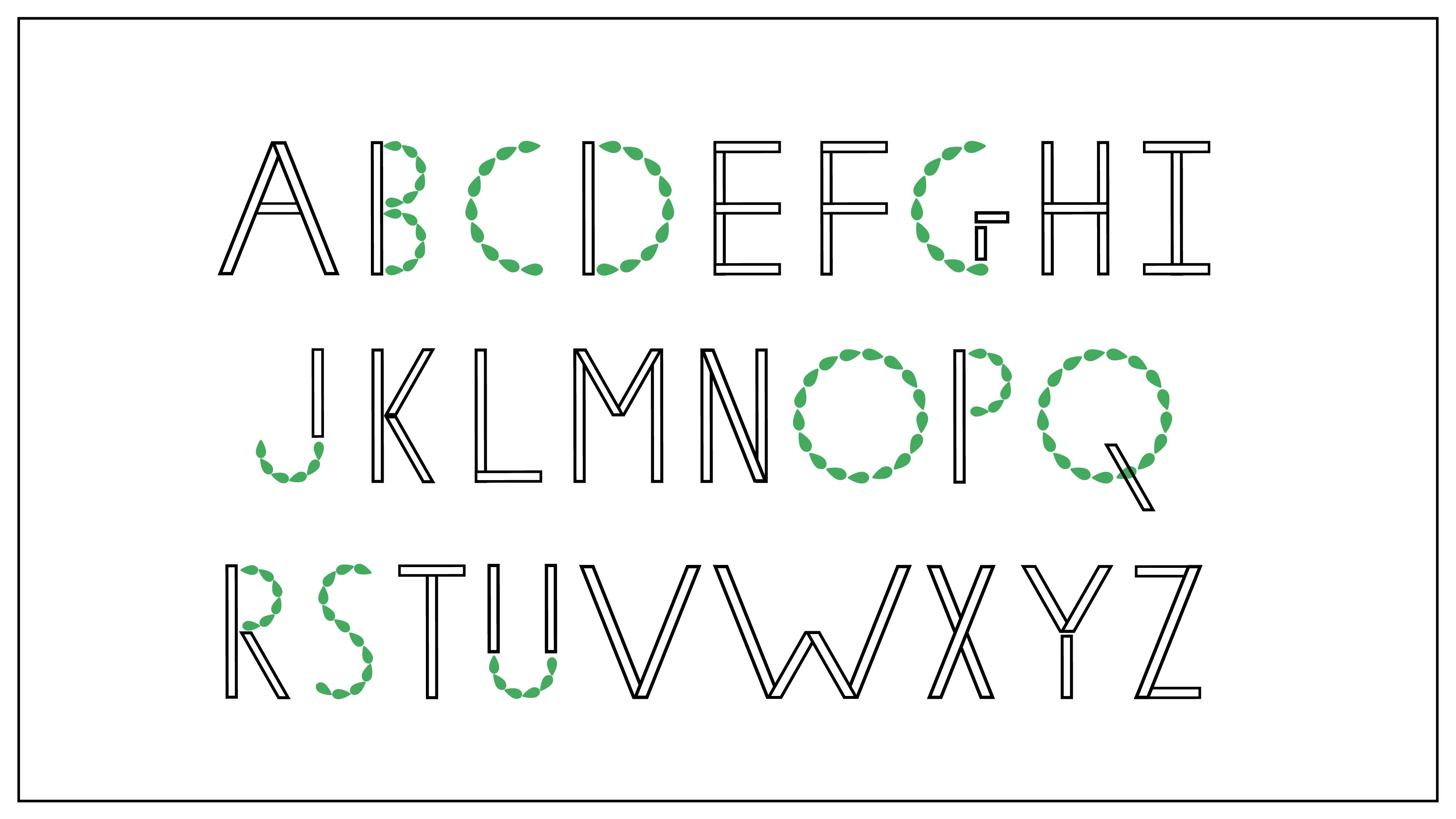
1. Einführung: Hallo und willkommen, modulare Topographie zu verletzen. Ich bin so eine Sharma, eine Motion-Designerin mit einem besonderen Platz in meinem Herzen für coole Typografie. Wenn Ihre totale Mama ist eine Art modulare Typografie ist ein großartiger Ort, um zu beginnen und Sie werden fantastische Typografie Arbeit Ihrer eigenen in kürzester Zeit. Diese Klasse lehrt die Grundlagen von modularen Typ zu machen, und wenn Sie nicht mit dem vertraut sind, was das ist, wird
es im Grunde genommen nehmen, wenn die Buchstaben aus einer begrenzten Anzahl von
Formen namens Modelle konstruiert werden . Also, im Wesentlichen, könnten
Sie einen Kreis verwenden und aufrecht. Ich gehe und mache eine ganze Schrift. Auf diese Weise sind
wir modulare Typografie. Die Buchstaben reichen von einfachen Formen in ein paar Linien von Autos, komplexere wurden mit komplizierten Formen,
Module, die schwer zu erkennen sind und viele verschiedene Module oft wollen. Sie wissen, Typenstücke basieren auf Körnungen auf jedem, den Sie lieben. Jeder Brief, entweder Allianz in das Raster von Millionen von Abschnitten Ihres Projekts durch diese Klasse wird sein, Ihren ganz eigenen modularen Typhus zu machen, einschließlich aller Spuren Buchstaben des lateinischen Alphabets. Dies mag überwältigend erscheinen, aber sobald Sie ein paar Formen haben, haben Sie bemerkt, wie ähnliche Buchstaben wie E L F I R auf der Schrift praktisch durch dieses Projekt kommen. Sie lernen grundlegende Informationen über die Zeitstruktur. Wie vereinfachen Sie die Illustration von dem, was Sie Gesichter auf ein wenig einfachen Adobe
eine modulare Schrift überall verwendet werden, wo Sie wollen. Abhängig von der Komplexität, können
Sie es für die Überschrift Teig, Spoelstra Spezifikationen, Druckmaterialien oder digital verwenden. Und wenn Sie sich ehrgeizig fühlen, könnten
Sie es sogar in einen gekämpft vor allem verwandeln. Es macht wirklich Spaß, und du kannst es nicht. Einige Papier real wurde nicht auf einige Illustrationen angehoben und eine politische Themen, um
2. Was ist ein modulares Typ?: Also bin ich so froh, dass du hier bist und du beschlossen hast, diesen Kurs zu nehmen. Bevor wir also tatsächlich unsere eigene modulare Schrift erstellen, lassen Sie uns ein wenig darüber reden, was Schriften modular macht und wie man mag, diese Modularität
sieht und was das alles bedeutet? Also, wie ich im letzten Video erwähnt habe, haben
Audioschriften einen riesigen Grat. Sie haben eine wirklich einfache Modelle, wissen
Sie, wo es so einfach ist. Das sieht eigentlich aus wie ein Gedanke, den Sie auf Ihrem Computer finden könnten, im Gegensatz dazu könnten sie wirklich, wirklich komplexe
sein . Wie für das wirklich genial damit, ist es das? Inspiriert von der Londoner Underground, wie diese Karte aussieht? Das ist also deutlich als Buchstaben erkennbar. Aber zur gleichen Zeit ist
es sehr viel eine Karte. Diese Modellierer sind so komplex, Sie wissen schon, mit den einzelnen Linien und Doppelaugen und alles und und komplexe Modelle können sehr
unterschiedlich voneinander sein . Aber diese, diese Schule, Steve Onkel über alles ist so kompliziert, wie die V's. Es ist so kompliziert, aber Sie können Dinge sehen, die wie sich wiederholende Formen sind. Weißt du, du hast eine säkulare Farm mit diesen Büchern, die immer wieder auftauchen, so wie das nicht ist. Oh, das ist ein Stichwort. Man konnte diese Ähnlichkeit dort sehen. Es gehörte immer noch dazu, Schriftkämpfer zu sehen, um ein Ei von dieser Schrift zu nehmen und von dieser Schrift, und ich habe sie in das gleiche Wort gesetzt. Sie würden wissen, dass das von zwei verschiedenen Typen ist. Aber wenn ich eine Reihe von Buchstaben vom gleichen Typ Gesicht nehme, sieht
es so aus, als ob es zusammen gehören soll, weil es als Einheit funktioniert. Weißt du, wie diese V und W, wo sie eine ähnliche Farm haben wie sie. Und so konnte man sehen, dass W im Grunde nur das ist, dass er zweimal wiederholt. Also, was wir durchmachen werden, ist, wie man diese Modularität erkennt und wie entworfen, dass es
anfänglich eine Einschränkung mit diesen
gibt. Zum Beispiel, wenn Sie etwas betrachten, das uns einfach ist, ist diese Art von einfachen ein Händler Schriftart ? Ich könnte etwas lange Worte schreiben. Vielleicht bekommst du einen Satz, bevor das anfängt zu verwirrend schwer zu sein. Aber je komplexer man geht, desto mehr muss es sein Es war wirklich sparsam und wirklich einfach. Ich meine, wenn ich mehr als das hier schreiben würde oder wenn ich etwas kleiner werden würde, würde
das wirklich,
wirklich schwer zu lesen sein. Und lassen Sie uns Ihnen hier
ein Beispiel geben. Dies ist eine schöne Schrift, die ich sagte, Sie können sehen, dass das sagt, Typ von. Ich fühle mich, als wäre das nett und groß. Aber wenn ich die Größe reduzieren sollte, schreiben ganze Sätze wie das wirklich gelesen wird. Wenn ich mir eine Art Handzettel Bank geführt oder ein Buch oder so etwas,
das ich einen Absatz hatte, würde
ich diesen Teil überspringen, wenn ich nicht gehen, um zu stehen und lesen Sie es darüber, wie Schönheit Schriften verursachen, das ist einfach zu verwirrend. Aber was geschrieben ist, ist, dass es alles Englisch ist. Es ist relativ einfach. Wenn ich das in die Zukunft verwandeln oder etwas, das leicht zu lesen ist, und das ist das gleiche Zeug, also ist es wirklich wichtig, wie Sie Ihre modularen Schriften verwenden. Es ist komplexer. Du gehst zu wirklich wichtigen. Denken Sie daran, dass Überschriften auf Banner und
großen, großen Typ ist, wo Sie Dinge wie diese verwenden möchten. Sie können es nicht vier Absätze verwenden, also gehen wir zurück zu dieser einfachen Schrift. Sie können sehen, dass das gleiche Rechteck eine Art von der Herstellung dieser ganzen Schrift ist. Sie können sehen, dass wir immer wieder die gleichen Einheiten verwenden, um die ganze Schrift zu erstellen. Und wenn ich dieses Stück von diesem Jake abschneiden würde, würde
ich das begreifen, oder wenn ich das wiederholen muss. Ich entscheidet, dass dies das eigene ausmacht und es viele reparative Formen hat, und Sie werden sehen, dass weniger immer für Morgenschriften gilt, weil Sie eine Einheit als
Modell verwenden und einen Haufen entwerfen und dass Sie das wiederholen und es drehen um und es etwas anders zu
gestalten, so dass man mit Briefen enden würde, die diese beiden anders aussehen, aber vielleicht etwas so kompliziertes betrachten und denken,
Oh, Oh, das ist ein normales Nachtgesicht, aber das ist es nicht. Die Sache ist, dass ich keinen Teil dieses Briefes lesen und ihn woanders anbringen kann immer noch etwas bekommen, das aussieht, als wäre es Teil desselben Typs Gesicht. Diese sehen alle sehr ähnlich aus, weil sie in einem ähnlichen Stil illustriert ist, und, weißt
du, da drüben ist etwas Zusammenhalt los. Aber ich kann diese Bar dieses K nicht nehmen und es in dieses l stecken. Das ist völlig anders, also werden Sie nicht versucht sein, das modular zu nennen. Aber du kannst es nicht kaputt machen. Sie können es nicht sehen, es sind Plaza-Stücke. Also ist es nicht behandelt Zeit, im Grunde genommen einen Haufen aus tatsächlichen Briefen und machte einige wirklich coole Illustrationen. Es ist wirklich schön, aber es ist einfach nicht Modellierer. Es ist also ein Teil der Ausschau nach denen, die kein Modell oder eine Schrift ist. Und das bringt uns zurück zu wie die letzte Art von modularen Schriften, die die Gitter-Basis sind jetzt zugeben, dass dieses Kastenraster, das wir hier dieses Meer haben, durch die Herstellung dieser Art von Diamantform
gemacht wird . Es ist so, als würde ich an verschiedenen Kreuzungen die Form unterschreiben, wenn jemand stirbt. Beschlossen,
Sie wissen schon, wirklich voran zu gehen, ehrlicher Schlaganfall. Mit diesen und anderen Orten haben
sie Spektakel Ding. Aber all diese Kreuze sitzen an einer Kreuzung von diesem Gitter, was diesen Brief macht. Es gibt also einen Punkt, an dem dieser Kreuzungspunkt in der Mitte des Platzes sitzt. Es ist immer an, wie eine Kreuzung, die bereits in diesem großen existiert. Ähnlich, für so etwas und Wunsch, verschiedene Teile dieser großen verschiedenen kleinen
Löcher zu füllen , macht
diese größte Formung all unsere Schrift und Sie können immer noch sehen, als ob sie nicht nur die Gitter. Sie stellen sicher, dass Teile von Buchstaben, die ähnlich aussehen wie diese Brokenness, dass Schlaganfall. Mal sehen, dass der Strom streichelt, dass e. Sie benutzen die gleiche Form immer wieder. Sie könnten es über die anderen ausfüllen. Wissen Sie, sie fügen dieses Dreieck auch für das Meer hinzu, oder sie könnten sich entscheiden, das E zu schließen, indem sie dies schließen, sie behalten diese Konsistenz und die Designkonsistenz ein großes und was Ihren
Modelltyp macht sah wirklich gut aus und gut gestaltet. Das werden wir hier drüben ähnlich ankommen. Weißt du, du musst nicht eins dieser etablierten Gitter nehmen. Du könntest deinen eigenen Griff machen und sie füllten einfach die richtigen Teile aus, um es zu den Buchstaben zu machen . Und es schreibt gerne wie eine Überschrift darin. Es würde Sinn für Sie machen, aber ein Absatz, wie ich schon sagte, würde einfach zu kompliziert werden. Also im Grunde, wenn Sie auf eine Schrift stoßen
und Sie nicht sicher sind, ob sie modular ist. Eines der besten Dinge, die du tun kannst, ist, dass du es dir ansehen kannst. Nimm das zum Beispiel. Sie können darüber nachdenken, dass es nicht so aussieht, als wäre es an irgendwelchen
Stellen aus der gleichen Neustartform gemacht. Aber dies wird zweimal wiederholt, um Ihnen sagen zu lassen, dass es auf den Kopf geht, um dieses M zu machen, und Sie sehen die gleiche sich wiederholende Form und so dass sich wiederholende Form das Modul ist und wir
eine Reihe von verschiedenen Modulen haben und, wissen
Sie, Sie sind alle auf verschiedene Arten angeordnet, um diese ganze Schrift zu machen und zu machen. Aber ich sitze hier und seziere das, und ich würde am Ende Puzzleteile sehen, und diese Puzzleteile sind miteinander verbunden, um verschiedene Buchstaben zu machen. Und diese Puzzleteile sind Montiels Gitter ein großartiger Ort, um zu beginnen, weil Gitter von
Natur aus sind , eine sich wiederholende Form, die gleiche Box wie hier drüben, diese Box Great. Diese Box wird immer wieder und immer wieder wiederholt, es ist das Gleiche. Ähnlich, mit dieser Form hier ist es das gleiche, immer wieder
wiederholt. Der Grund für Schriften modular ist, weil Sie in der Lage sind, die gleichen Formen zu nehmen und
sie an bestimmten Orten zu wiederholen , um etwas, das ein wenig anders aussieht, und Sie können eine Reihe von anderen Puzzleteilen nehmen. Setzen Sie sie in verschiedenen Konfigurationen zusammen und Sie am Ende mit verschiedenen Buchstaben und Rastern. Luft so ein großartiger Ort, um zu beginnen, weil Gitter von Natur aus die gleiche schlagende Form immer
wieder sind . Wenn du es fühlst, fühlst du dich immer in der gleichen Form, oder du richtest deine Form immer wieder an diesem Gitter aus. Sie haben automatisch etwas, das eine schlagende Form ist, was wir wollen. Weißt du, wir wollen etwas, das wir in Stücke zerlegen können, und das wird dir großartig geben. Nun, da wir herausgefunden haben, wie Modularität funktioniert, gehen
wir zur eigentlichen Typografie über und wie Typografie funktioniert, wie ihre Struktur ist. Wie soll man eigentlich dieses Alphabet nehmen? Alle Buchstaben ein schwindelig und lernen, sie alle in diese Art von modularen
Puzzleteile zu sehen , so dass Sie beginnen können, Ihre eigenen zu entwerfen
3. Die Struktur der Typografie: Nein, ich benutze hier einen Haufen Illustrator, und das kann wirklich überwältigend werden. Aber wenn wir tatsächlich in die spannende eigene Schrift springen, werde
ich durch, Illustrator, all die Grundlagen, all das einfache Zeug, das du wissen musst. Wenn Sie überhaupt keinen Illustrator kennen, Sie
nicht überwältigt von dem, was ich hier mache. Dies ist nur, um zu erklären, wie alles funktioniert. Jetzt, wo wir die Modularität herausgefunden haben, gehen
wir zur Typografie über. Das coole an dem lateinischen Alphabet ist, dass das ganze Alphabet, ich meine, alle 26 Buchstaben. Sie können alle in zwei Arten von Strichen geraden und gekrümmten unterteilt werden. Jetzt gibt es drei Arten von geraden Strichen. Du könntest horizontale haben, bequeme, und du könntest diagonale haben. Und gekrümmte können offen oder geschlossen sein. Und im Grunde, mit diesen fünf Arten von Strichen, können
Sie jeden Buchstaben auf Englisch aus machen. Also lasst uns das jedes Mal eine Chance bekommen. Das ganze Alphabet hier, richtig? Und so ist das Ihre Schriftart. Das ist Andiwal Glanz. Aber ich konnte jeden Buchstaben nehmen und ihn in diese Puzzleteile oder
Striche C zerlegen . Wir haben H aus zwei diagonalen Strichen und einem horizontalen Strichen gemacht. Es gibt eine vertikale wollte gebogene Striche öffnen und ähnlich sein. Es gibt nur einen Öffnen-Kurvenbereich und sehen. Und Sie können das gesamte lateinische Alphabet so aufbrechen. Das Ganze ist aus diesen Puzzleteilen gemacht. Das gesamte lateinische Alphabet kann so aufgeschlüsselt werden. So wie J u und s alle diese offenen gebogenen Striche verwendet. Richtig? Also haben Sie dieses J und öffnen Armstrong ist mit einem vertikalen gepaart. Oder verzweifeln Sie auch ein bisschen. Vertikale und s ist zu Öffner Striche mit einer Diagonale. Und so lassen Sie uns einen Blick auf, wissen
Sie, einige Dagnall-diejenigen, die A und Z. Er war die Daigle-Schläge und repariert mit diesen horizontalen geraden Strichen ähnlich mit em. Und weißt du, da gibt es dich, die sie mit geraden diagnostiziert haben. VW als Nächster. Sie brauchen niemanden anderen. Sie haben nur diagonalen Straßenstriche und K und warum sie sind ein bisschen ein besonderer Fall, denn obwohl sie alle diese diagonalen Striche wie die Luft immer noch diagonalen
Striche verwenden . Okay, aber wenn Sie eine gesuchte Schrift entwerfen, müssen Sie vorsichtig sein, wenn Buchstaben wie diese , die eine bestimmte Art von Strich verwenden. Aber vielleicht gibt es die gleiche Länge für den gleichen Grad der Kurve auf und sind die gleiche Größe weil lassen Sie uns einfach einen Blick darauf werfen. Wenn du ein sehr schönes Sterben entworfen
hast, weißt du, Designschule, Dad will dich und du willst es in all die Briefe setzen, die ich Module benutzt habe, die du einfach so lange richtig
machst und du kannst es in all diese stecken Briefe und du kannst
wie
ein Z.machen wie ein Z. Weißt
du, du hast deine Enden und deine VWs und Exes, die jeden anderen benutzen, den
du kennst , du hast sie. Was passiert, wenn du verfallen könntest, oder warum? Warum braucht langwierige kleine und auch K.
Kann das nicht in K setzen, denn was passiert, wenn man wirklich versucht, K aus einem von
diesen zu machen ? Ich habe immer noch einen Schuss. Wenn du versuchst, eine davon aufzupassen, wirst
du mit einer riesigen K gute Größe enden, was du? Das ist eine große, große K. Sie betrachten, vergleichen Sie das mit der Größe Ihres VW-Nexus, und Sie sind nicht wirklich in der gleichen Nähe mehr. Was passiert, wenn man ein Wort mit dieser Schrift buchstabiert? K ist größer als alles andere, was wirklich,
wirklich schlecht aussehen wird . Also, was Sie tun ist, Sie stellen sicher, dass Sie Buchstaben wie diese haben, die kleinere
Längen oder Größen von der gleichen Art von Strichdesign,
ein anderes Modell für sie oder Italien verwenden Längen oder Größen von der gleichen Art von Strichdesign, . Irgendetwas glaubt wirklich ähnlich. Also, als ob ich über die diagonalen Schriften erwähnte. Nehmen wir einen anderen Ort, wo das Problem auftreten könnte. Sie haben einen offenen Kurvenstrich. Dies wird viel Platz im lateinischen Alphabet verwendet, zum Beispiel im Meer oder behindern. Aber das Problem hier ist, dass, wenn du C und P wärst, die gesamten Wettenden die gleiche Länge haben wie deine Kurven. Schlaganfall allein ist eine wirklich andere Ereignisse, wissen
Sie. Es ist schnell die gesamte Höhe des Buchstabens in C, aber nur verbringt halb gestorben Brief in Schlüssel. Und so gibt es ein paar Buchstaben, die dieses Problem in PB haben und es nimmt die halbe Höhe von einem Buchstaben ein,
und in C,
D und Gnimmt
es die ganze Höhe des Buchstabens und in C, D und G ein. Jetzt könnten Sie sagen, warum das ein Problem? Es ist erledigt. Offener Bordsteinschlag. Entwerfen Sie einfach ein Modul, das funktioniert, ist ein offener Fluch Schlaganfall. Und ich sollte in die richtigen Briefe kommen. Okay, nun, lassen Sie uns das eine Chance geben. Was passiert, wenn Sie entwerfen? Weißt du, du hast dieses schöne Kurvenmodell hier drüben, okay? Entwickelt dieses Audio, und Sie wollen es überall verwenden, als offene Auto Hub wird im englischen Alphabet verwendet. Nun, wenn du das gerade entworfen hast
und dann so bist, okay, ich muss voll sein. Lassen Sie es jetzt. Also werde ich es einfach in voller Länge schaffen. Nun, das sieht schrecklich aus. Wenn Sie versuchen, ein Meer daraus zu machen, oder ein D sind, dass es viel zärtlicher aussehen wird als all Ihre anderen Wettenden, und es wird nicht so gut aussehen. Sie müssen also sicherstellen, dass ein anderes Modell entworfen wurde, das nicht im gleichen
Design-Sinn wie Ihr kleines funktioniert , aber entworfen wurde, um in dieser Größe zu arbeiten. Es gibt nur zwei Stellen im lateinischen Alphabet. Nur zwei Buchstaben, die geschlossen Vorhang Strich O und Q jetzt in einem 26 Buchstaben Alphabet verwendet, zwei Buchstaben ist nicht sehr viel. Das ist 1 30 das ganze Alphabet. Nun, wenn 1/13 so ein kleiner Bruchteil von Ihrer ganzen Schrift anders aussieht als ein anderes Treffen, wird
es nach dem Seltsamen suchen. Nehmen wir an, Sie beginnen Wort mit O que Wie Oktopus oder Königin. Es könnte ziemlich cool aussehen. Ich bin der Geist, die Hauptstadt. Aber was passiert, wenn O. R. Q. mitten im Wort
auftauchte? Es wird sich nur anschauen. Sie müssen also sicherstellen, dass das offene Bordsteinmodul, das Sie machen möchten, sicherstellen, dass das Job-geschlossene Kurvenmodul in der gleichen Welt in der gleichen Sprache funktionieren sollte . Das sieht so aus, als gäbe es einen offenen Kurvenstrich und es gibt eine geschlossene Kurve, und sie sehen aus, als ob sie in die gleiche Zeitfläche gehören. Wenn Sie also anfangen, seine Sachen zu entwerfen, ist
Designkonsistenz der Schlüssel. Wenn dein Zeug nicht konsistent ist, wird
es einfach schlecht aussehen. Wie, was passiert, wenn Sie eine offene Kurve haben? Stroke Sieht so aus, aber Ihre Kleidung erste Reihe sieht so aus. Es wird einfach wirklich fehl am Platz aussehen, wenn Sie anfangen, Dinge so gewünscht zu buchstabieren . Konsistenz ist der Schlüssel. In ähnlicher
Weise geraden Strichen entwerfen
Sie beigeraden Stricheneinen schönen vertikalen geraden Strich. Und du bist wie, OK, ich bin damit fertig. Ich werde es einfach nach innen drehen und meinen horizontalen geraden Strich leicht peasy machen, wie das Problem damit ist, wenn ich nur meine vertikalen Striche benutze und sie mit,
du weißt schon,
einfacher schwarzer Linie kombiniere du weißt schon, . Ich habe meine Fünf, die ein Alter machen. Aber was passiert, wenn ich es versuche? Verwenden Sie diese beiden Sehnsüchte, um h ich am Ende mit einem
wirklich, wirklich breiten h. Es sieht irgendwie seltsam aus. Es sah nur aus wie ein Alter. Und es gibt andere Briefe, die das auch benutzt haben. Du bist leichter f sicher. Ages werden wirklich breit Wenn Sie am Ende versuchen, die gleiche linke oder das gleiche verwenden Sie nur auf seiner Seite für eine horizontale Meerenge Gauner gekippt. Du willst also sicherstellen, dass deine Höhen und dein Verstand und alles
richtig funktionieren . Du hast also Lockerung. Du hast absolut Recht. Das sieht so viel besser aus, wenn es nur die Hälfte der Geburt von Ihrer Größe
ist, es fängt an, wie eine anständige Schrift zu sehen. Nehmen Sie alle diese Buchstaben, zum Beispiel, E f h l t. Und sehen Sie alle diese horizontalen geraden Strich verwendet, all diese Darlehen und groß. Damit ich die gleiche Mom entwerfen konnte, die du in all diese Briefe gesteckt hast, und es sollte funktionieren. Aber es gibt einige spezielle Anwendungsfälle, wenn es um diese horizontalen geraden Striche geht. Du hast G, wie ich. Jeanne. Ich benutzte diese horizontalen Streifen manchmal gebrochen. Und im Fall von GM haben
Sie eine vertikale. Das ist das gleiche als horizontale, Ihre vertikale, dass Ihr Design wahrscheinlich diese Höhe haben wird, weil all diese Buchstaben sie in dieser Höhe verwenden. Aber G, es braucht eine kürzere. Und dieses hier haben wir nicht manchmal der Grund, warum ich das sage, ist, weil ich uns diese
Schriften ansehen . Das sind eigentlich einige Schriftarten, die ich g und ich bin. Und schauen Sie sich dieses G. In diesem Fall verwendet
es einen kürzeren Hub horizontal und vertikal und in diesem Fall wird nur
Kurvenschlag öffnen . Aber wir bestellen einfach etwas, das Sie nicht brauchen. Eine vertikale Straße hier. Hier drüben will
es überhaupt keine horizontale Straße benutzen. Wir haben nur eine vertikale Straße eins. Also abhängig von Ihrer Schrift und je nachdem, was Sie es wie Ihre G My
Change gestalten möchten . Das Gleiche gilt für I. In einigen Fällen war
ich nur ein vertikaler, gerader Schlag. Aber manchmal wissen Sie, einmal eine Bar, der Arzt unten. Und dafür brauchen Sie eine horizontale Straßen. Rocca geht es gut und manchmal könnte das dasselbe sein. Aber nicht auf der Seite mit dem High Charton. Aber in einigen Fällen möchten
Sie vielleicht etwas anders gehen. Design weise, Ihre Autos von der Straße, Seile sind dünner als die vertikalen geraden Striche. Ihr Design kann sich also ändern, was vollständig von Ihrer Schrift abhängt. Und welche Art von Design Ihre Arbeit auf, Aber denken Sie daran, dass diese Luft, einige spezielle Fallbuchstaben und Sie müssen möglicherweise einige spezielle Module für sie entwerfen. Jetzt kommen wir zum Licht des speziellsten Falls. Das ist dieser kleine Spiral-Typ, den ich entworfen habe, nur um Ihnen eine Idee zu geben, wovon ich
spreche , Ihre speziellen Anwendungsfälle, wenn Sie Sachen wie warum que que Sie wissen alle diese in
Farbe haben ? G A. Ich all diese, die sich manchmal gewöhnen, aber Sie wissen, dass diese Art von lassen Sie uns an vielen Orten gewöhnen. Sie könnten ein cooles,
dekoratives Modell wie dieses entwerfen und es an all diesen Orten anschließen. Und der Grund, warum ich sage, dass Sie wahrscheinlich sollten, obwohl Sie eine sehr leicht
mit Ihrer Diagonale auf Ihrer Seite entwerfen könnte , ist bis eins. Möglicherweise möchten Sie dieses dekorative Element an mehr Stellen als nur dem
Minimum verwenden , wo es benötigt wird, denn je mehr Orte Sie Modell für den Typ verwenden, desto mehr wird es erstellt. Das Design Konsistenz über den gesamten Typ ist. Wenn Sie also anfangen, Buchstaben sind Wörter zu schreiben, wird
es so aussehen, als ob es sich in der gleichen Schrift und in derselben Welt sehnt. Wenn ich also meinen Pyro-Typ mitnehme und ihm „Warum „oder „K „oder „Q „und „Jeans A „und „ich... sieht
er so aus, als ob sie in derselben Nähe gehören, ? So könntest du so etwas machen und mit etwas Coolem enden, wenn ich einfach
damit arbeiten würde. Okay, das ist eine Arbeit. Aber der einzige Grund, der zusammen arbeitet und es sieht so aus, als ob es in die gleiche Welt gehört, ist weil ich den gleichen Spiral-Typ wieder benutzt habe. Geh einfach etwas Polieren. Ich meine, diese Diagnoseschläge sind nicht jedes Mal der gleiche Winkel, und das werden wir durchmachen, aber du kannst ihn so benutzen.
4. Gestalte Module: so ist die Zeit für uns endlich gekommen, Module zu machen. Wie ich im vorherigen Video erwähnt habe, gibt es Feuer grundlegende Arten von Strichen, und es ist eine gute Idee, ein Modell pro Hub zu erstellen, wenn Sie anfangen und dann
alle benutzerdefinierten Modelle erstellen , die Sie auf dem Weg benötigen, Sie möchten beginnen mit einem geraden horizontalen Strich, einem vertikalen Straßenstrich, einem diagonalen, geraden Strich, einem offenen Kurvenstrich und einem geschlossenen Kurvenstrich. Sobald Sie diese an Ort und Stelle haben, können
wir damit beginnen, Zollstriche zu Ihrem Modell Skin zu machen. Sieh
mal, wie du es willst. Wenn Sie für das Team starten möchten, ist
das OK. Sie können mit einem künstlerischen Thema beginnen, wenn Gothic oder Art Deco. Oder Sie können einen zentralen Fokus wie etwas Zufälliges wählen, vielleicht Wolken und entworfene Schrift um das. Wie ich im vorherigen Video erwähnen würde. Es ist völlig in Ordnung, wenn Sie nichts über Illustrator wissen, der in diese Klasse kommt. Aber für die Zwecke dieses Videos, fangen
wir auf dem Papier an. Alles, was Sie brauchen, ist Bleistift und Papier. Ich schlage vor, mit jedem Team oder Thema zu beginnen, mit dem Sie sich entschieden haben. Du musst es nicht tun. Dies ist nur zum Spaß, Sie können rein dekorativ gehen. Das ist
auch kein Problem, und diese Zeichenmodelle zu machen, von denen Sie gesprochen haben. Sobald Sie diese haben, würde
ich vorschlagen, sie auszuschneiden und sie in verschiedenen Konfigurationen zu platzieren, um zu versuchen,
die Buchstaben zu machen . Wenn dir die Art und Weise gefällt, wie die Dinge laufen und du das Gefühl hast, dass du genug Module hast, ist
fünf gut. Wenn Sie das Gefühl haben, zusätzliche Module wie kürzere Diagonalstriche für K zu machen und warum oder wenn Sie spezielle dekorative Module machen wollen, wie ich am Ende des letzten
Videos hatte , um vielleicht am Ende Ihrer Hinweise oder als Akzente auf Ihren Augen zu verwenden, Dies wäre die Zeit, das zu tun. Sie können für so viele Module gehen, wie Sie wollen, also schlage ich vor, nicht zu über Bord zu gehen. Aber ein Minimum von fünf ist erforderlich. Wenn Sie feststellen, dass Sie stecken bleiben, schlage
ich vor, ein Thema zu sprechen. Es muss gar nichts zu kompliziertes sein. Sogar etwas so einfach wie Blätter wird dio, vielleicht das Team wie Blätter. Sie hätten ein oder zwei Modelle, die deutlich Blatt wie sind, und der Rest würde als einfachere Akzente dienen, vielleicht ähnlich in der Farbe zu verlassen oder einfach nur ist eine schöne, kostenlose Farbe, um die Sie Ihre gesamte Taipeh gestalten können. wie immer Weniger istwie immermehr. Wenn du das Gefühl hast, dass du zu viel in deine Schrift
steckst, wirst du es wahrscheinlich tun. Ich könnte später schwer zu lesen sein. Sobald Ihre Module alle entworfen sind und Sie sie in Ihre verschiedenen Buchstaben gesetzt haben und Sie wissen, wie alles aussehen will. Machen Sie ein Bild von jedem Modul separat mit Ihrem Telefon oder einer Kamera, von der Sie bequem Bilder auf Ihren Computer hochladen können. Von dort aus werden
wir es zu Illustratoren bringen, damit wir anfangen können, es digital zu gestalten.
5. Gerades Stroben erstellen: Jetzt, wo wir unsere Modelle auf Papier entworfen haben, werden
wir in Illustrator springen. Ich werde Schritt für Schritt alles durchgehen, was du brauchst. Wenn Sie also mit Illustrator ein wenig vertraut sind, könnte
dies singen, aber langsam für Sie. Aber wenn Sie völlig nackt waren, Illustrator, werde
ich alles durchgehen, was Sie brauchen, um Ihr eigenes modulares Tempo zu bauen. So sieht der Home-Bildschirm aus. Wir werden voran gehen und drücken, neue Schaltfläche
erstellen. Nun, das ist meine Schnittstelle. Ein Illustrator. Sobald Sie über Ihre Bilder von Ihrem Handy oder Ihrer Kamera bekommen, möchten
Sie sie in Illustrator zu bringen. Dafür gehen
wir zu einer Datei Ort oder Sie können die Shortcut-Shift-Steuerung P verwenden. Platzieren Sie es einfach. Da ist ein Foto. Wie Sie sehen können, habe
ich ein Foto gemacht, das nur eins von jedem Modell hat. Ich werde dieses Bild als Referenz verwenden, also gehe ich zu meinem Ebenen-Panel direkt hier. Wenn Sie eines dieser Panels benötigen, können Sie zum Fenster gehen und auf das Paddel klicken, das Sie benötigen. Ich möchte zu meinem Ebenen-Panel gehen und ich werde hier schnell verdoppeln, was es
Referenz sein wird , und ich werde diese Ebene jetzt suchen. Ich kann es überhaupt nicht bewegen, und das wird wirklich hilfreich sein, weil wir andere Dinge darüber hinaus machen , die
fortlaufend zu bewegen,damit das nicht mit uns kommen wird. Ich werde diese Schaltfläche drücken, um eine neue Ebene zu erstellen, und ich werde anfangen, meine Module und Illustrator auf diese Weise zu machen. Es sei denn, Sie wollen, ist ein
sehr, sehr einfach Sie werden mehr benötigen als nur das Rechteck-Werkzeug oder die Ellipse, um Sie werden etwas mehr benutzerdefinierte benötigen. Wenn Sie einfach ein Rechteck benötigen, konnte einfach auf das Rechteck geklickt werden, und Sie könnten ziehen und machen, was Größe Tatsache mir gesagt wird, dass Sie wollen. Wenn Sie ein perfektes Quadrat machen wollen, nur trocken Hit Verschiebung zur gleichen Zeit und Sie sind Platz wird perfekt sein. Ebenso können
Sie zum Ellipsen-Werkzeug wechseln, wenn Sie jede Ellipse abschleppen möchten, die Sie erneut möchten. Wenn du dich verschieben
würdest, machst du einen perfekten Kreis. Wahrscheinlich werden Sie mehr brauchen als diese grundlegenden Formen,
und das ist, wo das Stift-Werkzeug ins Spiel kommt. Alle diese Buchstaben in Klammern, die neben dem Namen erscheinen. Wenn Sie den Mauszeiger über ein Werkzeug bewegen, sind die Tastatur-Shocker, die Sie verwenden, um es wirklich schnell zu verwenden . Zum Beispiel könnte
ich einfach auf die Tastatur pinkeln und ich bekomme mein Benzin. Der Weg zum Stiftwerkzeug funktioniert ist, dass ich auf eine Stelle klicke, an der ich einen Punkt beim Ziehen machen möchte, um die nächste auf den Linienformen zwischen diesen Punkten zu machen. Auf diese Weise kann ich das machen, was ich will. Und wenn ich auf den ersten Punkt zurückkomme, sehen
Sie diesen kleinen Kreis und ich klicke wieder und es wird eng geformt. Wenn ich es offen lasse, wird
es weiterhin versuchen, das nächste Bit von der Form weg von hier zu ziehen. Wenn Sie Kurven Dinge mit mental machen möchten, können
Sie auf ziehen klicken. Diese geben Ihnen diese Griffe. Diese Griffe werden als beschäftigt A Handles auf bezeichnet, und Sie können sie verwenden, um die Kurve von etwas zu steuern. Diese mathematischen berechnen, was die Krümmung von der Linie vor uns sein wird, und Sie bekommen schnell und Drachen, um diese Kurve zu machen, und Sie könnten unsere Chips so machen. Seine so wollen wieder, Ich verbinde mich, um diese Werkzeuge auszuwählen, Ich esse die oder Sie können auf das Auswahlwerkzeug klicken. Dadurch wird alles ausgewählt, was Sie wollen. Wenn Sie entfernt werden, können
Sie darauf klicken und es wird die gesamte Form zusammen klicken. Dies unterscheidet sich von dem Direktauswahlwerkzeug, dem Sie einzelne Punkte beim Bewegen nur auf eigene Faust treten können. Aber Sie können mit diesem Wahlzehen nicht tun. Ich kann keinen einzelnen Punkt bewegen. Ich muss die ganze Form verschieben, und Sie können die Rücktaste oder Löschen auf Ihrer Tastatur verwenden, um alles loszuwerden. Also fangen
wir mit diesen grundlegenden Werkzeugen an, unsere Schiffe ein wenig zu verfolgen. Ich möchte meine horizontalen vertikalen und diagonalen Striche. Drei einfache Rechtecke ohne Farbe in der Mitte streichen nur Linien. Also gehe ich zu meinem Rechteck-Werkzeug auf. Ich werde etwas über das hinwegziehen. Ich werde es jetzt loslassen. Haben Sie ein Rechteck, aber ich möchte Justin Umriss in Illustrator. Eine einfarbige Farbe in der Mitte wird als fehlgeschlagen auf einem Umriss bezeichnet wird als Strich nach oben. In meiner Farbe sind meine Farbfelder Panel. Ich kann sehen, dass diese Erfüllung auf diesem ist ein Schlaganfall. Wenn ich auf das Feld klicke, kann
ich es in die Farbe ändern, die ich sein wollte. Und wenn ich nicht füllen will, kann
ich einfach kein Gefühl auf. Und jetzt haben wir eine Form ohne Gefühl und keinen Schlaganfall. Ich will, dass mein Schlaganfall schwarz
ist, also werde ich Schlaganfall treffen. Und was dann? Schlag schwarz. Wenn ich nun mein Auswahlwerkzeug drücke, das nur V Tastatur ist und wegklicke, kann
ich sehen, dass es einen Strich um ihn herum hat. Ich kann die Dicke des Strichs ändern, indem ich auf die Strohplatte gehe und den Wechsel auf eine
Gewichtszunahme wartet . Ich schwinge meinen Schlag dicker. Im Moment hat
mein Schlag scharfe Ecken. Wenn ich darauf klicke und die Ecke
ändere, bekomme ich runde Ecken. Für den Moment möchte
ich ihnen eine scharfe Ecke halten. Wenn ich eine ähnliche Technik verwende, um meinen vertikalen Hub zu machen, wird
die Dicke dieser beiden nicht gleich sein. Ich möchte konsequent bleiben, also werde ich es nicht so machen. Ich werde dies duplizieren, ändern Sie es so, dass es die richtige Länge ist, um früher zu duplizieren, wenn Sie darauf klicken. Ich werde Option oder Ault auf der Tastatur nehmen und ich werde diese Doppelpfeile bekommen. Das bedeutet, dass überall dort, wo ich diese neue Form nehme, die Leute dupliziert haben. Also werde ich einfach wegziehen und es gehen lassen und ich werde eine andere Form haben. Ich kann das zu meinem senkrechten, geraden Strich überführen. Ich werde es um 90 Grad drehen. Ich wollte perfekt vereinte Abschlüsse sein, also werde ich mich verschieben. Du machst es perfekt und gut. Richten Sie es aus und ich möchte die Breite überhaupt nicht ändern. Ich möchte nur die Länge ändern. Aber weil ich so vergrößert bin Outbreak jetzt zeigt es mir nur diese diagonalen Steuerungen auf dem mit Kontrolle. Weil das so lang ist. So wird es wieder aufgenommen. Ich werde Befehl plus auf Mac oder Control Plus auf einem PC drücken. Und jetzt bin ich nah genug, dass ich diese vertikalen Manipulatoren sehen kann. Also werde ich nur ziehen das machen es lange genug. Also, jetzt ist mein mit die gleiche geblieben wie meine horizontale. Wenn ich schwenken möchte, kann
ich die Leertaste drücken, die das Handwerkzeug vorübergehend aktivieren würde, greifen und bewegen, wenn ich den Griff dauerhaft aktivieren möchte. Ich traf H und ich kann immer in der Hand Werkzeug sein, aber Raum ist ein netter Trick. Kann Befehl minus drücken, um zu verkleinern. Ich nehme diese und alte und ziehe sie hierher. Nun, wenn ich das einfach um ein wenig rotiere, werde
ich diese flachen Tasten nicht so bekommen, wie ich es will. Also werde ich Z kontrollieren, dass wir zoomen, damit ich sehen kann, was ich tue. Ich gehe zu meinem schiere Tool und ich werde auf Gehe zu Hit Enter klicken. Jetzt kann ich das Haus kontrollieren, das ich teilen wollte. Ich wollte einen 30-Grad-Winkel teilen. Ich werde überprüfen, um sicherzustellen, dass es so aussieht, wie ich es wollte. Guter Schlag. OK, jetzt ist mein Titel perfekt geteilt. 30 Grad. Ich wollte
jedoch umgekehrt sein, also möchte ich mein Reflection-Tool verwenden. Ich kann O auf der Tastatur verwenden oder ich kann hier wieder zu meinem Reflektierungstool gehen, ich werde die Mitte treffen. Ich muss eintreten und es wird vertikal reflektiert. Ich könnte auch horizontal reflektieren, wenn ich will. Ich möchte eine Kopie davon machen, weil ich will, dass eine Seite diesen Weg geht und die andere Seite diesen Weg geht. Also würde ich Copy drücken. Und jetzt muss ich, dass ich mein Auswahlwerkzeug drücken könnte. Das ist V auf der Tastatur. Ich bewege das weg und jetzt habe ich meine zwei diagonalen Striche in beiden Richtungen. Jetzt setzen meine diagonalen geraden Striche auf meinen horizontalen geraden Strich auf meinen vertikalen
Straßenstrich sind alles perfekt mit dem Teil. Sie sind perfekt geschoren, wo sie auf ungefähr dem richtigen Land sein müssen. Wir können diesen Führer immer so anpassen, wie wir es im nächsten Schritt tun werden.
6. Vereinfache Illustrationen und gebogene Stroben: jetzt gesendet, um unsere gekrümmten Striche zu machen. Jetzt werde ich mit der Blatt-Sache gehen, die Dr. Aber aus dem vorherigen Video,
das ist meine schreckliche Skizze aus dem Mietvertrag. Das erste, was ich tun werde, ist eigentlich einzigartig. Eine Blattform. Dafür werde
ich mein Stiftwerkzeug benutzen, komm rüber zu diesem Teamstück. Ich werde nur ein Standard-Grün nehmen, nur damit ich sehen kann, was ich tue. Es ist nicht der Begriff weiß, und ich werde die beschäftigten Griffe verwenden, die ich sprach, um ein halbes Blatt zu machen, weil ich es
perfekt reflektieren konnte , so dass ich Shift verwenden konnte, so dass es perfekt gerade steht und erstellen, Aber ich fühle mich wie es ist perfekt halb Blatt. Da dies los wird, werde ich V schlagen, so dass es seine eigene hält sogar als eine offene Form und ich werde wegklicken. Jetzt sehe ich, dass ich ein halbes Blatt habe, aber ich brauche die andere Hälfte. Also werde ich das wieder nehmen Hit Oh, für mein Reflexionswerkzeug. Ich werde eines dieser Enden verwenden, weil dies der Zugang ist, den ich
reflektieren möchte . Ich würde hier Option oder Schraube treffen. So wurde es perfekt an diesem Rand reflektiert. Ich will ein Exemplar, damit ich es kopieren kann, und ich werde einen perfekten Häuptling haben, der hineinzoomt. jedoch sehen, Ich kannjedoch sehen,dass dies immer noch nicht geschlossene Form ist, denn wenn ich ausgewählt habe, werden verschiedene Hälften separat ausgewählt. Ich kann immer Drachen zusammen gewählt werden. Aber ich möchte ein Blatt kaufen, um eine warme Form zu sein, so dass ich es manipulieren kann, wie ich will. Also, dafür werde
ich in zu wiegen, um die Kanten zu finden, wo diese Teile verbinden. Ich werde mein direktes Auswahlwerkzeug nehmen, das mein Andi ist, ziehe diese beiden Punkte zusammen, ich werde Steuerung J für Join treffen. Nun, diese beiden Punkte wurden zu einem verbunden. Wenn ich das mit meinem Direktauswahlwerkzeug auswähle,kann
ich sehen, dass es ein ganzes Schiff ist, das ähnlich gemacht wird,
wenn ich zu diesem unteren schwenke,muss
ich diese beiden auch hier verbinden. Wenn ich das mit meinem Direktauswahlwerkzeug auswähle, kann
ich sehen, dass es ein ganzes Schiff ist, das ähnlich gemacht wird, wenn ich zu diesem unteren schwenke, Dies sind zwei getrennte Pfade. Jemand traf mein direktes Auswahlwerkzeug, ziehen Sie über nur diese beiden Punkte, die
Kontrolle J.hatten Kontrolle J. und jetzt ist dies auch ein Punkt. Ich werde wieder verkleinern, damit ich sehen kann, was ich über dieses ganze Blatt schlecht mache. Wählen Sie dieses Blatt, Andi, tauschen Sie meinen Strich und fühlen Farben, indem Sie dieses kleine Symbol hier. Jetzt habe ich keinen Schlag auf diesem Blatt. Und nur um mein Blatt zu füllen sieht ein wenig aus. Obwohl irgendwo, um zu meinem Direktauswahlwerkzeug zurückzukehren, passen Sie dies
einfach ein wenig an, indem Sie die Iraker verwenden. Nun, ich mag die Art, wie das aussieht, aber ich habe das Gefühl, dass dieser Tipp zu scharf ist. Also werde ich dies mit meinem direkten Action-Tool auswählen. Das ist ein auf der Tastatur, nicht mein Auswahlwerkzeug. Also werde ich mein Direktauswahlwerkzeug verwenden, um einen dieser beschäftigten Griffe zu greifen und ich kann ihn wegbewegen. Aber ich wollte ein perfekter Winkel sein, damit ich ihn im gleichen Winkel in die andere Richtung bewegen konnte. Also hatte ich eine Verschiebung, die sich perfekt 45 Grad entfernt bewegte. Ich mache das Gleiche auf der anderen Seite. Jetzt siehst du dieses kleine, was ich hören kann, ich kann das nehmen und ich könnte es benutzen, um mein Blatt ein wenig zu weich zu machen. Klicken Sie weg. Ich mag diese Form. Ich denke, es würde sich schön wiederholen. Ich kann die Farbe von diesem Grün manipulieren, aber ich möchte Mit meinem Farbfeld, Ich kann sie auf Rot,
Grün oder Blau in diesem manipulieren . Oder ich kann hier nach oben gehen und dies in Farbton,
Sättigung,
Helligkeit oder sogar schöne Farben ändern Sättigung, . Ich werde HSP wirklich schnell setzen. Auf diese Weise kann ich einfach den Farbton ändern, aber ich möchte bleiben. Das grüne Spektrum kann verändern, wie gesättigt meine Arenen sind, wie hell es ist. Das ist ein gutes Grün. Ich denke, es ist nicht zu hell, nicht zu übertrieben. Aber es ist schön und lebendig. Würdest du wegklicken, weil mein Leben fertig ist? Eine gute Faustregel ist, wenn Sie etwas machen, das Sie einen Illustrator
mögen, ändern Sie es nicht sofort. Wenn Sie es ändern möchten, verschieben Sie es um irgendetwas. Machen Sie eine Kopie, indem Sie ault und ziehen, die wiegt. Ihre ursprüngliche perfekte Form bleibt unverändert, und wenn Sie diese eine durcheinander bringen, haben
Sie immer eine andere weggezogen. Später, wenn Sie sich entscheiden, dass Sie mehr haben, als Sie brauchen, können
Sie es einfach tun. Also werde ich jetzt versuchen, meine offene Kurve zu streicheln. Also will ich mein kopiertes Schiff nehmen. Könnten Sie hineinzoomen, damit ich sehen kann, was ich tue? Ich möchte das herunterskalieren. Aber wenn ich diesen diagonalen Pfeil benutze, wird
er meine Form abflachen und die perfekte Form ruiniert, die wir gerade gemacht haben, so dass er
wieder Shift schlägt , damit er perfekt nach unten skaliert. Das scheint eine gute Größe zu sein. Ich werde das drehen. Ich habe nicht meinen Anfang hier, aber ich wollte von unten so gehen, wie sie nicht normal gehen, wäre nicht die Natur. Also werde ich es hier drüben vollkommen flach haben. Und im Laufe der Zeit wollte
ich mich auf, gehen perfekt flach bis zu diesem Punkt in einem perfekten Halbkreis. Da ich jedes Mal perfekte Winkel machen möchte, werde ich etwas verwenden,
das das Erscheinungsbild Panel genannt wird,
was wirklich praktisch ist, um das das Erscheinungsbild Panel genannt wird, Kopien von Dingen mit perfekten Messungen zu machen. Ich werde zu diesem kleinen Effektknopf gehen es verzerren und transformieren und gehen, um zu transformieren . Ich werde diese Vorschau anzeigen, damit ich sehen kann, was ich mache und ungefähr acht Kaffees machen kann. Sie können nicht sehen, dass meine Acht diese jetzt anrufen, weil sie alle an einem Ort
übereinander sind. Wenn ich diese verschiebe, können
Sie sehen, dass ich jetzt viele verschiedene Kopien habe. Ich möchte, dass sie sich vertikal nach oben bewegen. Ich will, dass sie in die andere Richtung gehen. Sie beobachteten sie, um einen bestimmten Winkel zu gehen. Wenn ich diesen Winkel genauer steuern möchte, kann
ich hier auf meine Scroll-Maus klicken, um das wirklich sehr genau zu ändern. Ich mag die Art und Weise, wie dies geht, um ein paar weitere Kopien zu machen, so dass es
perfekt geht . Wenn Sie jetzt Nacht, können
Sie sehen, diese sind perfekt Topping Boden. Haben Sie eine schöne Reihe von Blättern, die sich wiederholen auf. Das kann mein perfekter offener, gekrümmter Strich sein. Also gehe ich zurück zu meinem engen Kurvenstrich. Ich werde einfach die Option hier verschieben, weil ich weiß, dass es so wieder funktioniert und ich
gehe zurück zu meinem Erscheinungsbild Panel. Es verwandelt sich so, dass ich wieder auf den Stil der Bücher zurückkommen und einfach mehr Kopien machen kann. Mai 16 sein. Ich möchte, dass meine 16. 1 perfekt auf meine 1. 1 abgestimmt ist, also werde ich dies ein
wenig ändern,
nur um wenig ändern, sicherzustellen, dass das passiert. 21.1 scheint hier der perfekte Winkel zu sein. Okay, ich werde mein Blatt zur Seite bringen, damit ich es nicht störe. Und wir werden meine Referenz später verstecken, weil wir damit fertig sind. Jetzt haben wir unseren geschlossenen Kurs. Der Schlaganfall ist offen. Ihr Strich sind vertikale, gerader Strich, horizontale, geraden Strich und Diagonale. Gerade Striche wirklich Kopien zu machen, wie wir entlang gehen. Aber vorerst mögen
wir diese Modelle. Also wieder, Band wird zur Seite schauen und einfach einfügen. Brauchen wir sie?
7. Erstellen der Buchstaben: Das nächste, was wir tun wollen, ist, dass wir expandieren wollen. Diese Shapes, wie Sie sehen können, die bei Strichen nahe
sind, werden beide von einem Darstellungsfenster ausgeführt und werden künstlich Kopien erstellt. Aber ich möchte, dass dies eine Form ist, also gehe ich zu einer Option ziehen. Also werde ich widersprechen, Aussehen
erweitern. Und jetzt ist mein Schaf mit dem Regisseur-Selektionswerkzeug auswählbar. Alle meine Leads werden ausgewählt. Ich werde dasselbe mit meinem geschlossenen Kurvenstrichobjekt machen, dasAussehen
erweitern, Aussehen
erweitern, und das funktioniert großartig. Das nächste, was wir sicherstellen müssen, ist, dass unsere Höhen alle perfekt sind. Also werde ich das Stift-Werkzeug verwenden, um ein paar gerade Linien verschieben zu lassen, und ich werde dieses etwas sehr leicht zu sehen färben, wie ein helles Blau. Und ich werde drei gleich weit entfernte Linien machen. Wie Sie sehen können, wenn ich ziehen halten Shift, es gibt mir einen kleinen Kerl, um sicherzustellen, dass ich die Läuse an Ort und Stelle geschnappt. Wir werden das als Kerl verwenden, um sicherzustellen, dass die Höhen all unserer Buchstaben in
jeder tatsächlichen Schriftart korrekt sind . Wenn Sie tippen, habe ich Tee gerade jetzt gedrückt, um auf die Art Werkzeug zu bekommen. Wenn Sie überhaupt etwas eingeben und Sie sicherstellen, dass es alle Hauptstädte ist, alles ist eine perfekte Höhe, indem Sie sehen, dass meine Leichtigkeit, meine unsere. Die Mittelpunkte dieser Buchstaben richten sich immer perfekt an diese mittleren Lichtkräfte aus. Meine Oberteile und Böden verbünden sich perfekt an den Enden dieser Linien, und wir werden sicherstellen, dass unsere modulare Schrift den gleichen Regeln folgt, damit wir später
mit ausgewählten Personen mitnehmen können . Schneiden Sie sie aus, fügen Sie sie auf eine neue Ebene ein und legen Sie sie ab, damit
wir sie nicht versehentlich wie unsere Referenz verschieben . Jetzt müssen wir sicherstellen, dass unser geöffneter geschnitzter Strich für unsere C und
D auf diese Höhe ausgerichtet ist , und sie sollten ihn treffen, verschieben und ziehen. Es ist also eine perfekte Höhe. Ich werde das gleiche tun mit meinem geschlossenen Kurvenstrich für meine immer ein Angeklagte kann an die Linien
schnappen. Wir brauchen einen offenen Golfschlag, der für Bienen in Frieden halb so hoch ist. Nehmen Sie es zu meiner Mittellinie, transformieren Sie auf dem Erscheinungsbild Panel, um sicherzustellen, dass es perfekt Kurven zu diesem Punkt gut . Scheint recht. Ich brauche Treibstoffkopien. So ziemlich weniger. Einige gut, diese fünf Exemplare zu machen. Das sollte richtig sein. Jetzt haben wir unser Halbgericht wieder einen Schlaganfall. Ich werde sicherstellen, dass Sie eine Kopie davon haben. Unverändert. Also jetzt haben wir unsere volle Höhe. Offener Autohub sind volle Höhe, nahe Gruppenhub sind halbe Höhe, offener Herzschlag. Wir brauchen auch unsere Fußversionen unserer offenen gebogenen Schläge. Ich werde meine aktuellen Schläge schnell aus dem Weg bringen. Jetzt kann ich an meinen Straßen arbeiten. Ich kann mehrere Formen gleichzeitig auswählen, indem Sie die Umschalttaste drücken. Ich werde diese kopieren, um sie zu unserem Führer zu bringen, um dies zu
fahren. Und jetzt sind wir ein wenig wenig hoch. Jemand zoomen und stellen Sie sicher, dass wir diese auf die Linie perfekt zu diesen Rändern verwenden. Ich will nicht, dass dieses extrovertierte Schwarz rumhängt. Ich möchte, dass der ganze Schlaganfall in diesem System lebt. Aber ich kann zu einem Strichfeld gehen und ich kann sagen, dass ich den Strich nach innen ausrichten möchte, damit nicht der ganze Strich in dieser Box lebt. Ich werde tun, es tat dies auch, so dass unsere Preise unverändert bleiben. Und ich werde grob beurteilen, wie lange ich das wünschen soll, abhängig davon, wie ich aus diesen beiden Strichen ein
H daraus machen könnte . Kopieren Sie das. Siehst du, wie mein Gesicht aussieht? Es sieht so aus, als wollte ich so weit weg sein, aber Schwester weit. Also werde ich das etwas kürzer machen. Das scheint richtig zu sein. Jetzt weiß ich, wie lange meine Autos sind. Straits schrieb, braucht mich reparieren unsere Diagonalen wirklich schnell. Ich werde das vorerst löschen, damit wir hier einen reparieren können. Ausgerichtet ein Zoll Verschiebung, machen Sie es größer, aber wieder ausgekleidet die Innenseite. Aber das hat diese Szene denken lassen, dass sie näher beieinander sind als diese, also muss ich sie manuell anpassen. Also für das, Ich muss einzelne Punkte eine Art von meinem direkten sexuellen Werkzeug oder eine schnelle auf diesem
einen Punkt auswählen , so nicht ausgewählt schnell diesen Punkt als auch. Jetzt werden nur diese beiden Punkte ausgewählt, die anderen nicht. Und ich kann das überprüfen, indem ich den richtigen Schlüssel und nur den boshaften Schritt bekomme. Jetzt werde ich nur sehen, dass dieser Wunsch der gleiche ist. Das sieht gut aus. Und ich werde den Schlaganfall um ein wenig reduzieren. Es sieht also gleich aus, selbst wenn ihre mathematische Wahnsinnige manchmal etwas geteilt hat sie weißer aussehen
lassen, als sie tatsächlich sind. Und so werden wir nur unsere Augen benutzen, um sicherzustellen, dass das jetzt so aussieht, werde
ich es duplizieren. Aber das ist ein sehr
weites A. Also denke ich, was ich tun werde, wird nicht die Schiere daran ändern. Ich gehe zurück zu meinem schiere Werkzeug eingeben. Nun, das ist zu viel Minusstand. Scheint richtig. Oh,
gehen Sie ein, um eine Kopie zu machen. Jetzt haben wir unsere diagonalen Straßenstriche. Jetzt, wo alles in der richtigen Höhe ist, können
wir tatsächlich anfangen, Briefe zu betteln. Und jetzt kommt der lustige Teil. Lassen Sie mich einfach anfangen, Briefe zu machen, in einem wissen Sie, wir müssen gerade Striche und einen horizontalen geraden Strich diagnostizieren, also werden sie Kopien davon machen und sie zu unserem Kerl bringen. Wir werden nur leben, bis du unser A machst. Ich will nicht, dass sich die Ecken davon zeigen, also werde ich sie ein bisschen näher
zusammenbringen . Und es stieg den Rücken im Wesentlichen zurück. Aber das hat keinen Unterschied gemacht. Weil die keine haben, Phil, sie sind transparent. Also, was ich tun werde, wird sie füllen. Nein, haben wir nicht. Ein Das sieht toll aus. Spritze. Ziehen Sie es, klicken Sie mit der rechten Maustaste und gruppieren Sie es zusammen. Und jetzt mit dem Auswahlwerkzeug nimmt
es immer ein a auf. Zusammen können
wir das beiseite bewegen, werden aufgehoben. Es ist wie eine Biene. Wir wissen, dass wir einen vertikalen geraden Strich brauchen, und diese Kurve wählt Bedürfnisse, um sie hier nach oben zu bringen. Ich hoffe, dass wir wollen, dass die Handgelenke unserer Briefe ungefähr gleich oder Fall . Natürlich
nicht das Gleiche, weil ich so breit wie ein sein werde, aber ich benutze es einfach als Führer. Das war gut. Gut. Genau so. Alle zusammen. Corbett, wir haben ein B wir haben bereits C für D. Lasst uns hier Streik zwei nehmen. Es ist gut. Zusammen haben wir ein d-Alphabet beginnt wirklich zusammen zu kommen. E Ich mag die Art und Weise, wie sich diese Linien schneiden. Also werde ich füllen, was auch immer es erfordert, um den Effekt zu erhalten, den ich will. Aber Sie können die Designs so ändern, wie Sie sie mögen. Je nachdem, wie Sie das unterschreiben möchten, können
Sie mit diesen sehr kreativ werden. Schön. Ich mache eine Kopie, weil ich einfach eine dieser Zeilen entfernen kann, um genug zu machen. Dafür brauche
ich keine Zehengruppe. Dies kann ich einfach doppelklicken. Ich gehe wieder in die Gruppe. Ich werde diese Stücke einzeln anklicken. Also werde ich das bewegen. Ich habe jetzt meine Frau für eine etwas andere G. Wenn Sie sich von unserem letzten Video erinnern, benötigt
G ein Modul, das nicht unbedingt die gleiche Höhe wie dieses hier ist. Sie könnten ein spezialisiertes Modell für so etwas entworfen haben. Habe ich nicht. Also werde ich nur die Höhe dieses Artikelmodells hier ändern. Und stellen Sie sicher, dass es aussieht, als hätte es den gleichen Hub wie alles andere, weil die Pipette Werkzeug, um den gleichen Effekt aufzunehmen. Wenn ich von einem dieser Bilder aufsehe, wird
es sich grün anfühlen. Genau. Fühlt sich grün an. Aber das ist gestreichelt. Inter streichelte schwarz. Ich will das nicht duplizieren. Dieses spezialisierte Modul legte es auf die Seite, um meine G zu machen Also jetzt, da diese ich diese neue Spezialisierung habe, legte eine Kopie davon und halten Sie es hier für den Fall, dass ich es wieder für Q me Seite
brauche. Ich könnte eine Reise leicht auf e schon 12 machen. Also geh zurück und mach eine Gruppe zu diesen Zwecken. Kopiere das an Mitch. Kann ich es erleichtern würde. Nun, halten Sie in der Mitte. Wir fahren das in die Mitte. Es ist Nacht. So wird er sehen, dass sich unser Alphabet hier wirklich bildet. Und dann können wir damit anfangen, Wörter dafür zu buchstabieren. Ich will meinen Anteil. Offene Kurve, Strich. Wir nehmen das einfach auf die Seite und benutzen mein vertikales Modell. Ich mag nicht, wie sich das hier überschneidet, also werde ich die Höhe-Tech-Schule ändern, die zusammen auch mit
Befehl G oder kontrolliertem G aufgewachsen ist, jetzt in der Lage zu weit diagonalen Modulen. Aber wir brauchen, dass sie für K. halb hoch also lass uns sehen, wie das für immer funktioniert. Tun Sie Seite davon. Was passiert, was? Sieht viel Tenor aus, nicht wahr? Gehen Sie also ein wenig zurück zu unseren zuverlässigen Direktauswahlwerkzeugen wie diesen Kanten in der modularen Pipette. Das, damit Sie den gleichen Schlaganfall bekommen? Immer noch eine kleine Nadel, also das ist wenig denken, das sieht gut aus. Du brauchst dieses Zuhause. Drehen Sie das horizontal. Eine Kopie. Ich versuche nur in die Polizei. Das ist Samuel Little 10 im Vergleich zum Rest des Briefes. Song würde eine kleine, stilisierte Wahl treffen und diese nur diese Enden ziehen, um ein wenig weiter weg zu sein. Im Moment esse ich den Pfeil nach rechts. Das sieht also aus wie das Richtige mit. Jetzt, wo ich ein anderes spezialisiertes Modul erstellt
habe, werde ich es hier speichern. Ich benutze es woanders. Ich? Warum? Mit dem e wieder für L. Jetzt können wir dieses Modell wieder für unser Ende verwenden. Einzigartig infiziert. Kopie davon. Probleme beim Ausrichten von irgendetwas haben. Sie können das Allianz-Panel hier benutzen, damit ich will, dass diese ihre Zentren verbreiten. Und ich möchte, dass sie alle ihre Spitzen ausrichten. Jetzt sind sie alle perfekt ausgerichtet. Ich hoffe nur, sie ziehen Verschiebung Dies habe ich ein perfektes ihn und was sie früher ausgefüllt wurden. Also fühle ich, dass ich will sieht gut aus. Und es ist ziemlich einfach. Ist dir klar, während ich diese durchmache, habe ich ein paar Regeln für mich selbst geschaffen. Ich fülle immer einen diagonalen Strich oder einen sich schneidenden Striche, wenn einige Linien durchscheinen, wenn ich ein seltsames Dreieck mache oder kubanisch die Mitte mache, aber ich lasse einen von ihnen durchscheinen, weil ich denke, es wird ein nettes, stilisierten Effekt. Aber ich ändere diese Regel nie und lasse sie nicht manchmal durchscheinen. Ich lasse sie nicht manchmal nicht durch ihre immer nicht durchscheinen. Das wiegt also. Wir bekommen immer die perfekte Schrift, die Sie wirklich nicht haben. Oh, es ist R P. Sie können unser stilisiertes Modul verwenden für Sind süß, diese eine Gute, Sie sind effektiv. Ich bekomme keine Kopie. Ich kann es in meinem Pinkel auf einem dieser spezialisierten Modelle argumentieren. Also, wie ich bereits erwähnt habe, ist dieses Fleisch weg, um ihre Striche mit Diagonalen verbunden zu öffnen. Aber das stimmt nicht immer. Es kann auch Open Corp Striche sein,
je nachdem, wie sie konstruiert sind. Glaubst du, ich werde mich drehen? Er ist nur ein wenig, so dass sie Preis aussehen, geben Sie mir genug Platz in der Mitte, so dass ich den Ruf dieser
einzelnen ändern könnte , so dass sie schön miteinander verbunden aussehen Hier ist etwas Tee ist sehr einfach auch. In der Tat könnte
es nur mit I Es gibt t Sie ist einfach ein J mit zwei Partikelaugen. Ich werde das einfach vergessen. Du weißt, dass V diese beiden diagonalen Linien zusammen sein wird. Also lasst uns einfach aufstehen. Wir nehmen Wohnmobil. Ich nehme die Linien, die an unserem Ende gemacht haben. Kopieren Sie diese mithilfe des Steuerelements. Sehen? Ich werde mit dieser Gruppe ausgehen. Beginnen Sie mit meiner B-Gruppe Control V einfügen, dass das behoben wird. Ich will, dass all diese Böden lebendig sind, also gehe ich zurück zu meinem Verbündeten und einem geschmeidigen Boden. Sie können unser Veto verwenden. Machen Sie auch unser X. Haben Sie
einfach eine Crossover, Ihren Sex. Die Videos sind sterilisierte Modelle. Warum? sah seltsam aus, er blieb wieder über das überlappende Look-Skript. Der Wunsch ist nicht aus. Das sieht eigentlich aus wie eine Bank auf der linken Seite. Auch wenn es nicht ist. Es ist eine seltsame optische Täuschung, also denke ich, dass ich meinen großen diagonalen Hub hier nicht benutzen werde. Es wird nur die kleinen verwendet und der gerade vertikale Hub kürzer zu machen. Warum? Zu denken, eine kleine Lücke zwischen sieht Art von cool zusammen auf einem, was übrig ist, ist das Meer . Ich werde diese einzelnen Linien lieben, damit sie versteckt werden. Füllen Sie das hier aus, sehen
Sie? Und da hast du es. Da ist unser gesamtes Modell, für das wir es schön auf einem neuen Gericht arrangieren können, um zu sehen, wie
alles zusammen aussieht. Gute Trefferschicht. Oh, für das Kunstbrettwerkzeug. Und könntest du ein neues Whiteboard machen? Vielleicht hier, X Y c Kopiere sie hier drüben. Es sieht wirklich cool aus. Da ist unser Angebot, aber unser kleines Blattmodell aus der Wette wieder. Wie ich bereits sagte, du kannst mit Blut gehen,